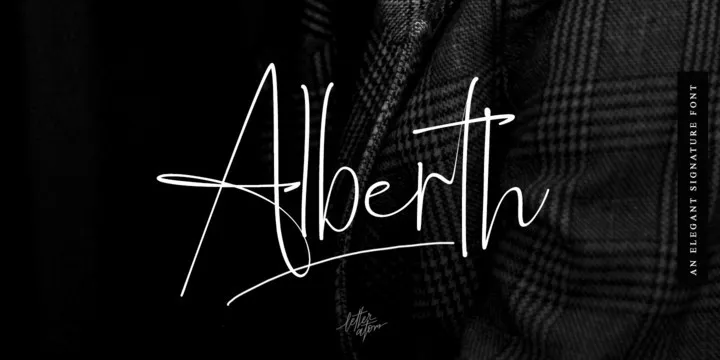
A Alberth Font é uma família elegante de fóruns para assinaturas, projetada com um estilo natural que transmite a autenticidade de uma escrita à mão. Seu design diferenciado e compartilhado pela Atom lhe oferece mais do que apenas beleza. Com 119 ligações elegantes, este conjunto de fóruns única proporcionará um toque luxuoso e sofisticado para qualquer projeto. A Alberth é perfeita para branding projetos, criação de logotipos, designs de casamento, postagens nas redes sociais, anúncios, embalagem de produtos, design dos produtos, selos, fotografia, água-marinhas e até mesmo convites e material de estação. Se sua próxima ideia gráfica precisa de um toque de escrita à mão, a Alberth é uma ótima escolha.